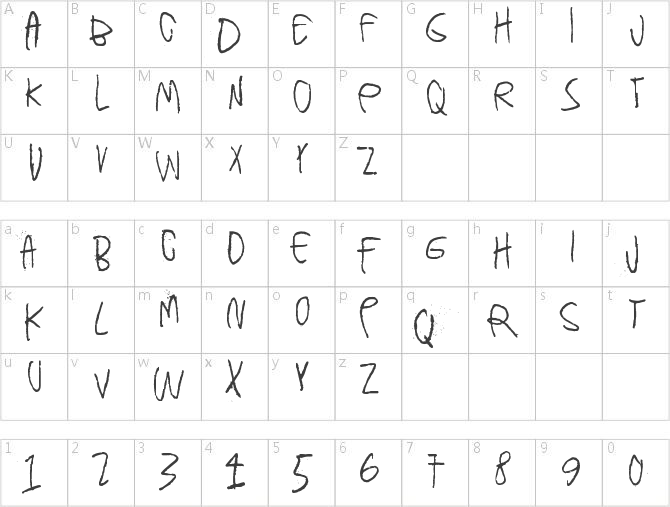
Can you ever see a whole circle 詳情頁
Can you ever see a whole circle字體字庫是一款讓人賞心悅目、百看不厭的英文字體,適合各類廣告和產(chǎn)品包裝設(shè)計應(yīng)用,字體大小0.06MB,格式為ttf字體,上傳用戶是373790005,作者/版權(quán)方為未知